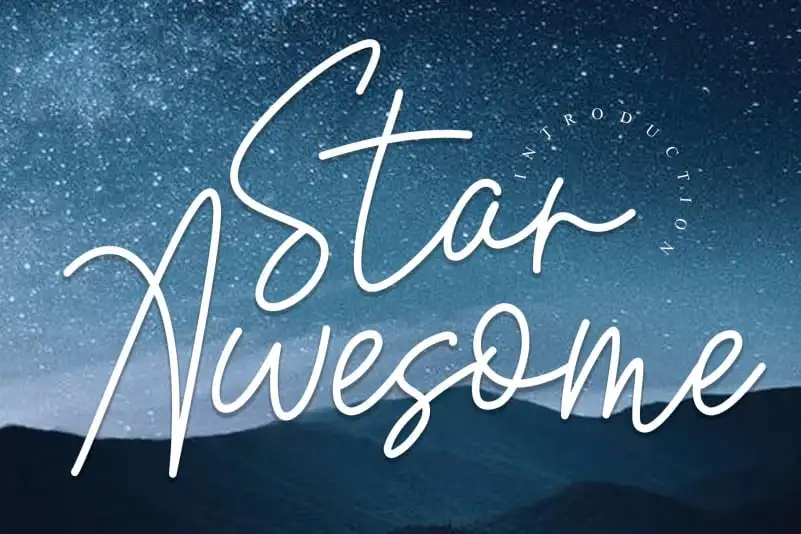
Star Awesome Handwritten Font – Fonte Grátis
Star Awesome Handwritten Font
Através deste download da nossa famosa categoria de fontes de escrita manuscrita, a fonte ‘Star Awesome Handwritten Font’ é mais do que simplesmente uma escolha de fonte; ela oferece uma experiência inovadora e única para qualquer projeto que você esteja trabalhando. Desenvolvida pela criativa equipe da designer creativeletter, essa fonte permite que seus projetos se destacuem com um estilo singular e personalizado. Com ‘Star Awesome Handwritten Font’, os designers podem criar texturas que transmitem uma sensação de amizade e descontração. Suas linhas fluidas e círculos arredondados oferecem uma forma suave e agradável, perfeita para textos em cartazes ou folhetos, mas também adequada para design gráfico sofisticado. Sua versatilidade torna-a ideal tanto para criações digitais quanto para trabalhos tradicionais. Estamos certos de que o ‘Star Awesome Handwritten Font’ irá transformar sua maneira de criar e se destacar no mercado de fontes, oferecendo uma experiência única e emocionante. Não perca essa oportunidade de revolucionar seu trabalho designando com um estilo único e personalizado.